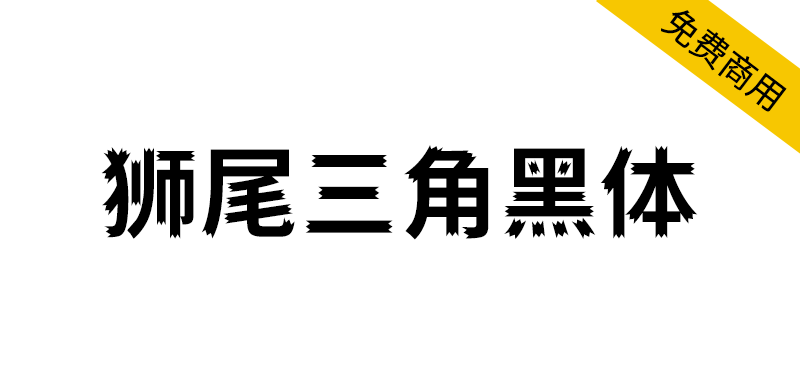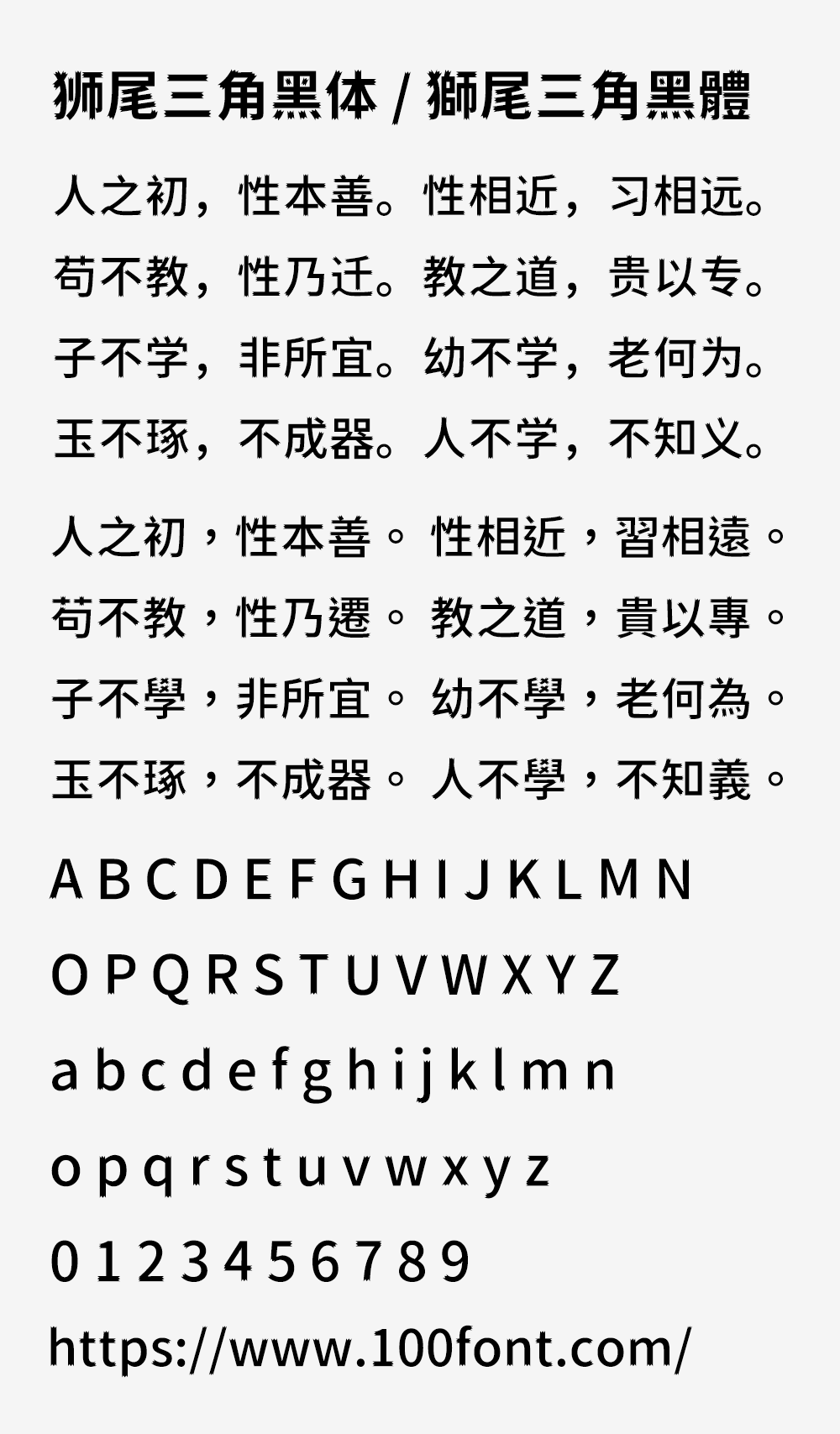
狮尾三角黑体基于思源黑体笔触开花和拔脚改造,更加简明现代化的字体。狮尾三角黑体的特色是「一」字的开头和结尾笔触由平头换成开花式的三个三角形。和思源黑体一样,有7种字重,支持简体中文、繁体中文、韩文与日文,可以免费商用,欢迎大家自由应用、自由优化、自由改作!
狮尾三角黑体和「狮尾三腿黑体」差别在有没有拔脚,「拔脚」就是会有较少的笔画,例如移除「口」字的左右下角会多出的短线条。有拔脚的字会较圆,但是会造成有些字因直接去掉腿后左右不平衡、左右不对衬的「悬空」问题。改使用「腿」系列字体就不会有这个问题。